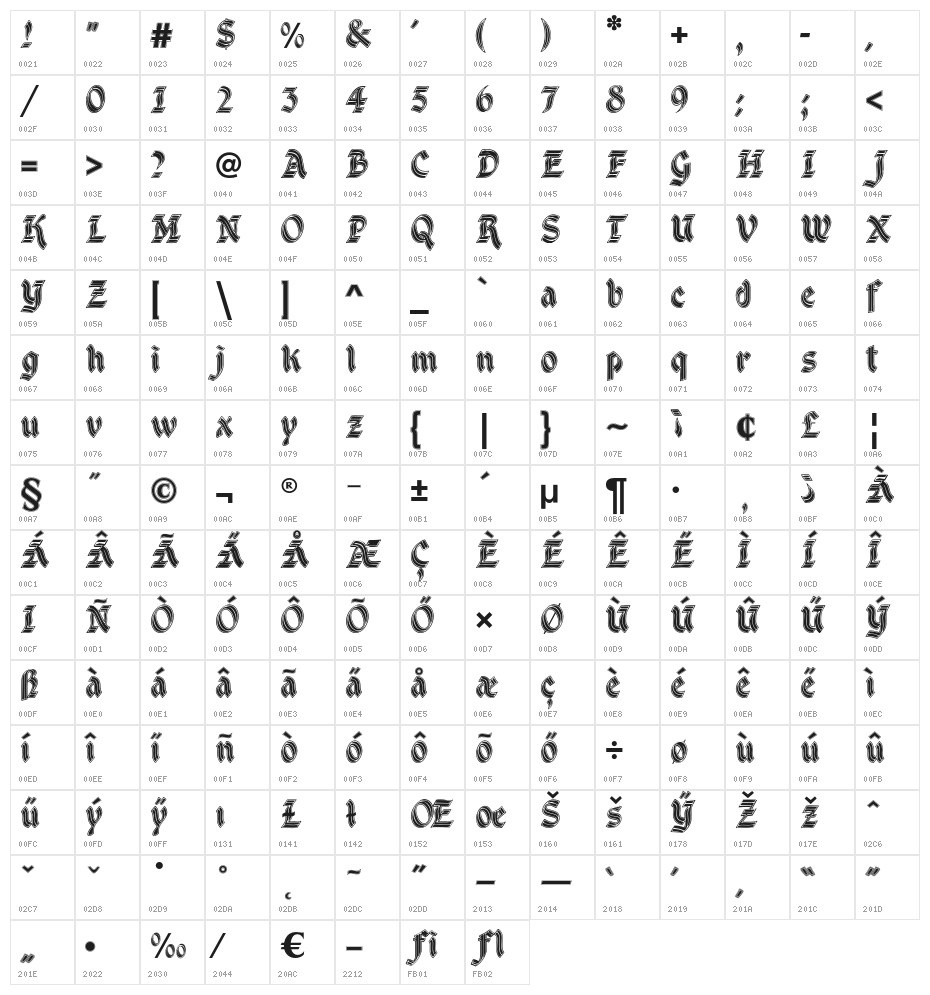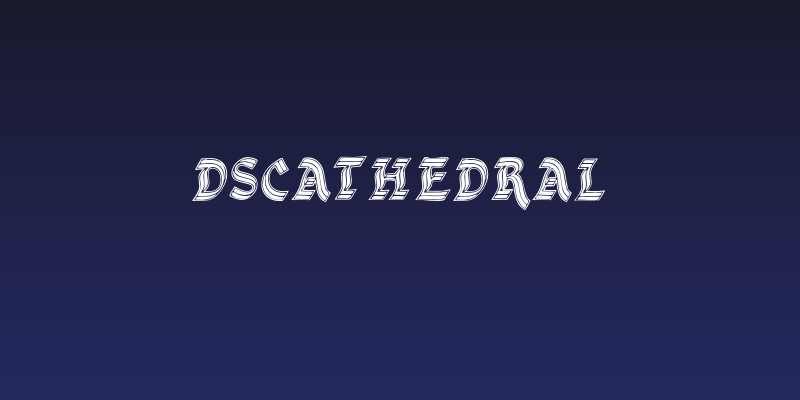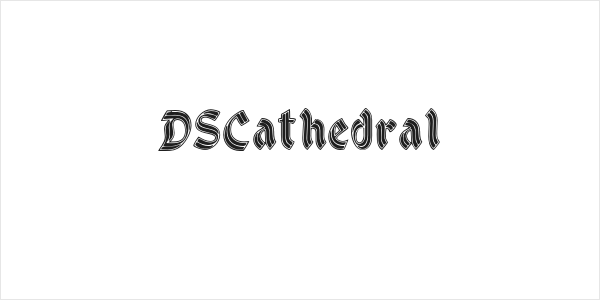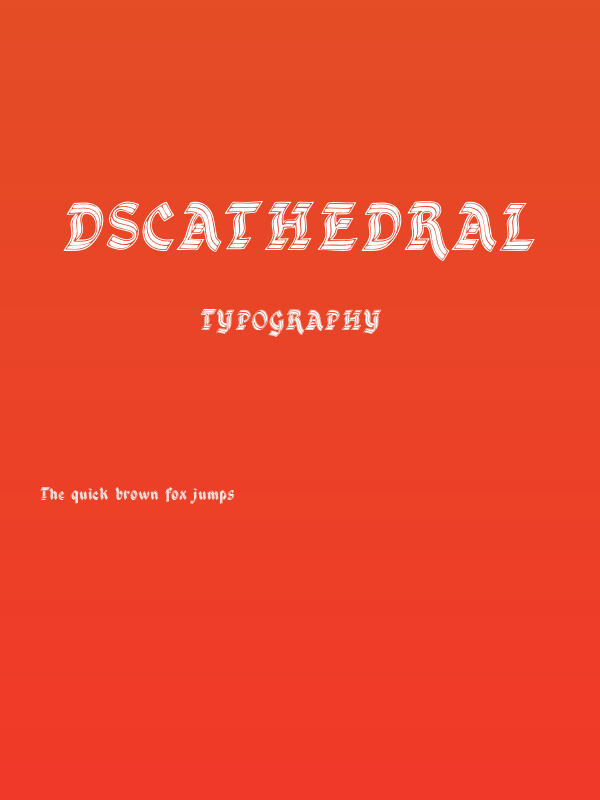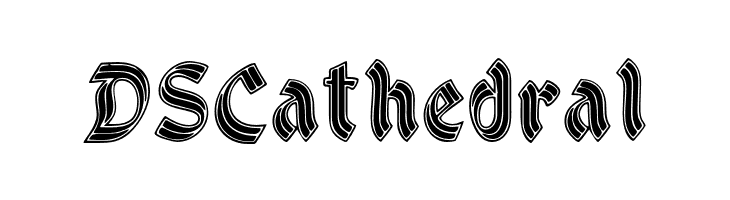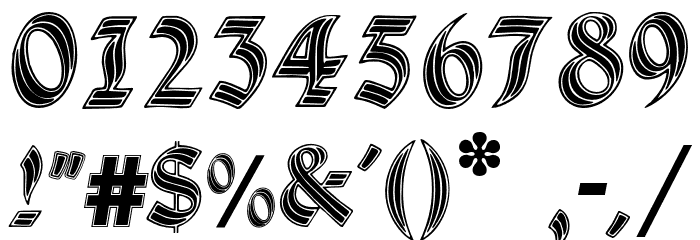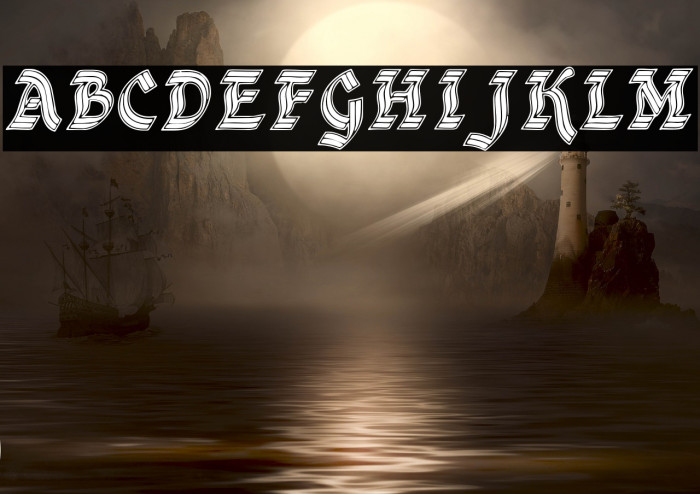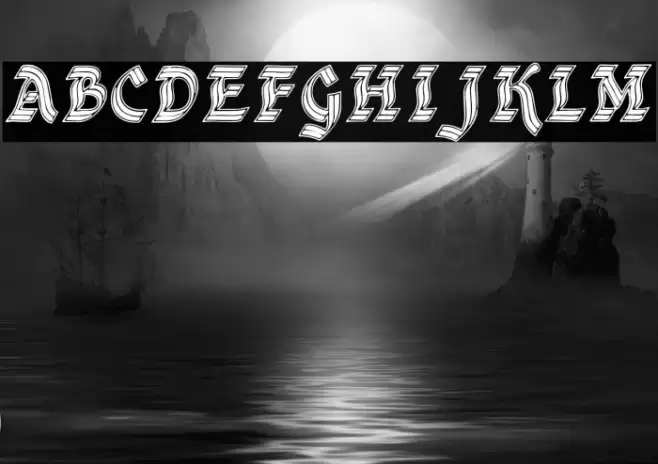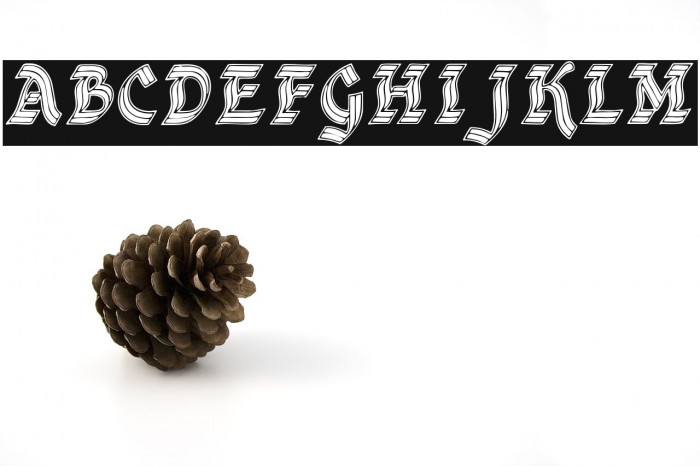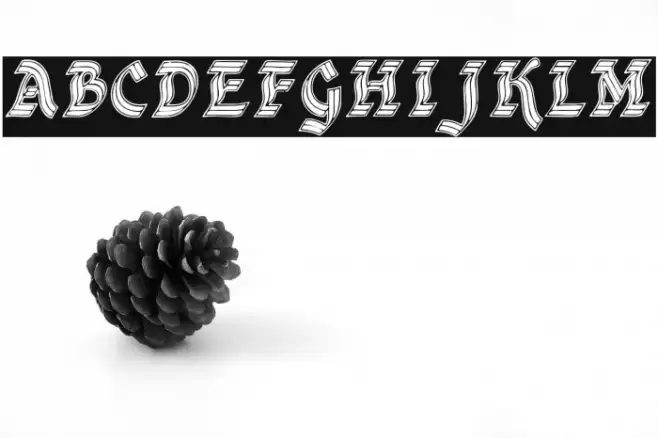
DSCathedral Font
| 推荐项目 | Ideal for projects that require a dramatic and historical touch, such as book covers, posters, branding for luxury products, or themed event invitations. |